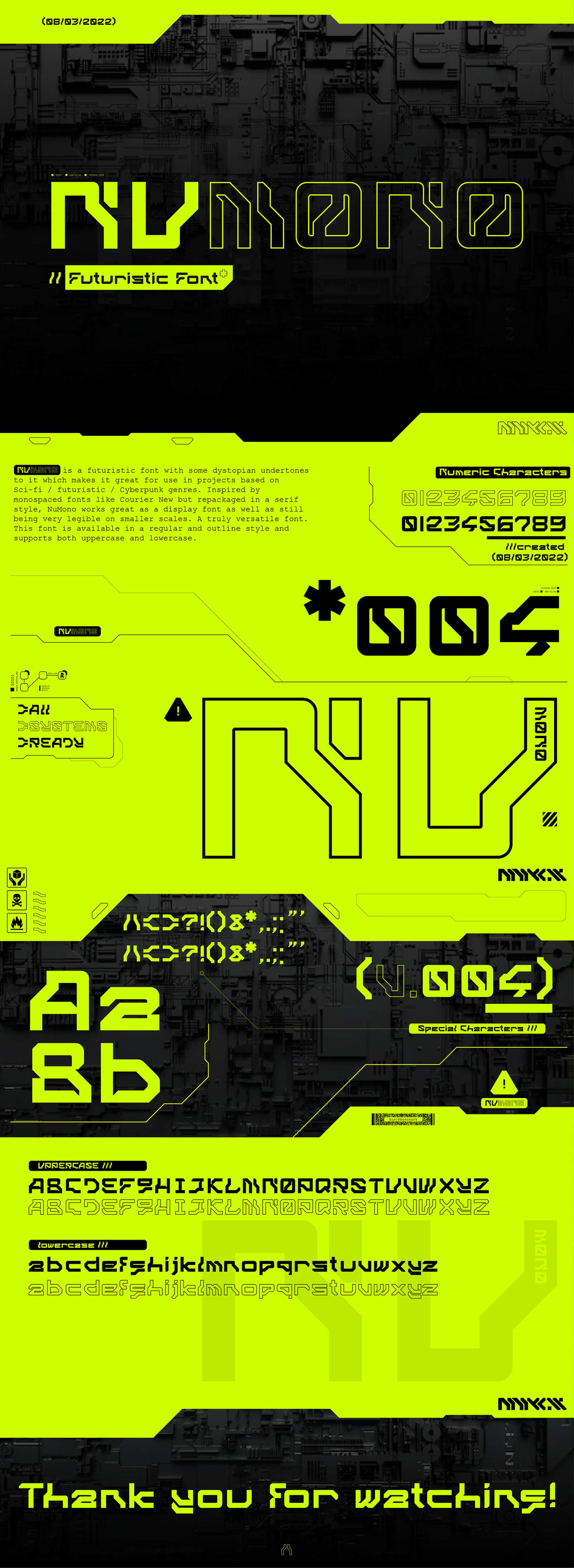
Шрифт NuMono (Caps)
Шрифт NuMono — футуристический шрифт с антиутопическим оттенком. Это делает его отличным для использования в проектах, основанных на жанрах научной фантастики/футуристики/киберпанка. В бесплатной версии прописные символы.